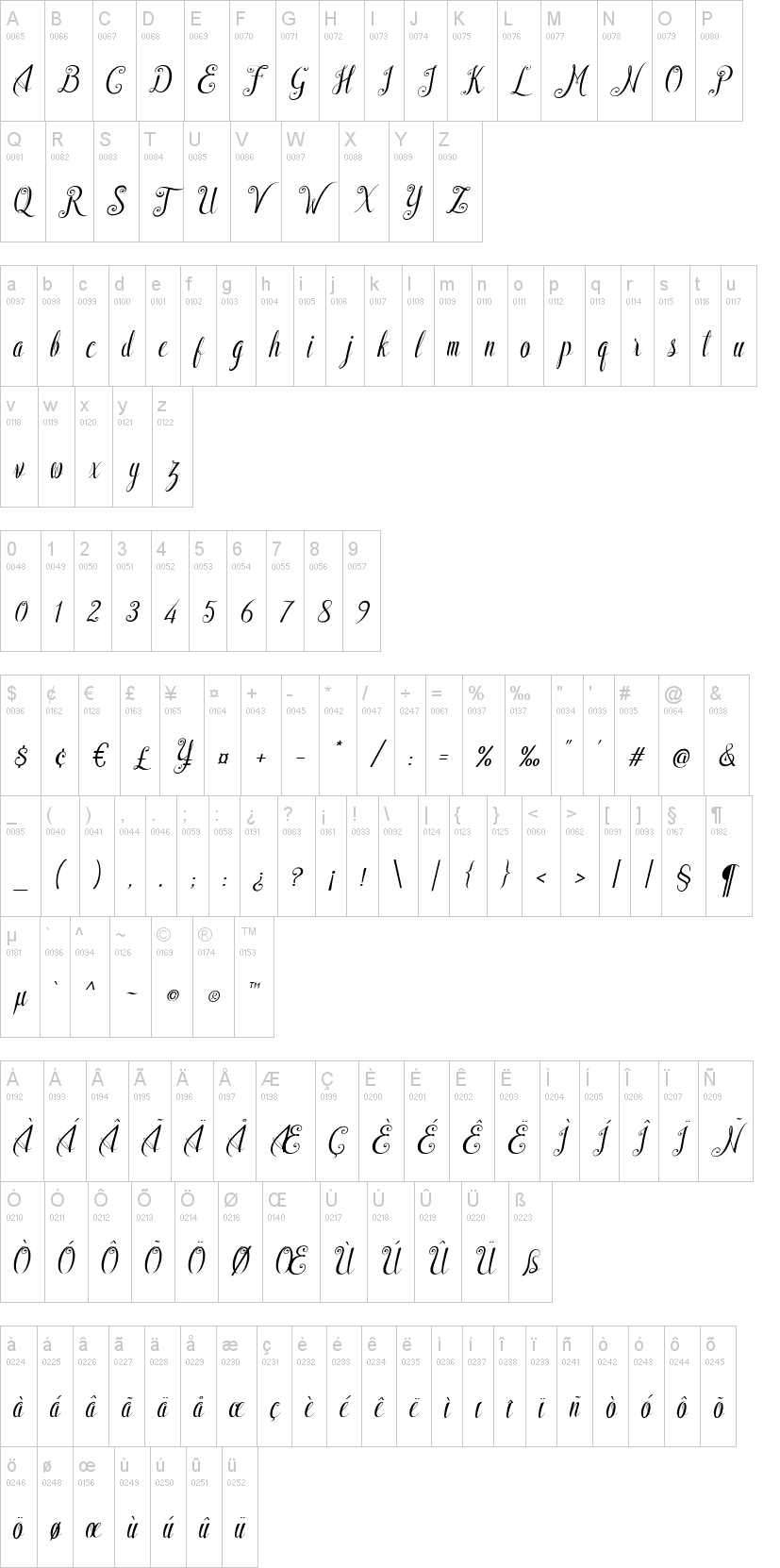
Shyntia Bella
Shyntia Bella 是一种华丽、优美的手写字体,由 Indonesian Creatives 设计。这种字体的风格类似于独特的手写书法,有着流畅、自然、优美的特点。Shyntia Bella 字体适用于各种设计项目,如海报、名片、印刷品、活动宣传资料等。它有着多种不同的字形和特殊字符,可用于设计出具有个性和创意的文本。这种字体的设计风格能够吸引人们的注意力,使设计更加独特和引人注目。Shyntia Bella 字体可在许多设计软件中使用,如 Adobe Photoshop、Illustrator、InDesign 等。
Shyntia Bella是一款非常不错的手写艺术字体,具有很好的视觉感,适合于文化类的宣传设计、商业类品牌的广告和产品包装设计以及个性化文字排版等较多场景。